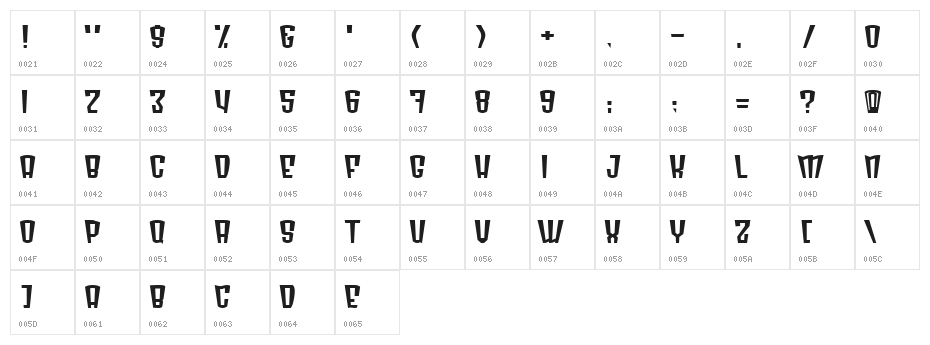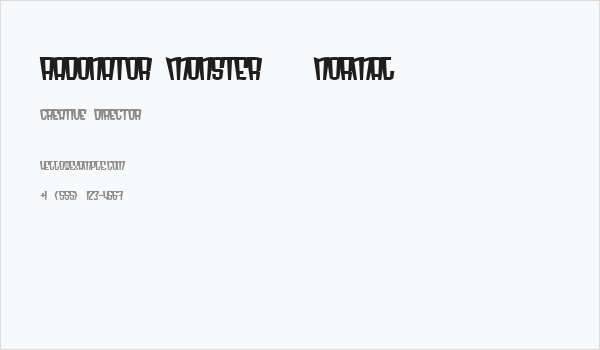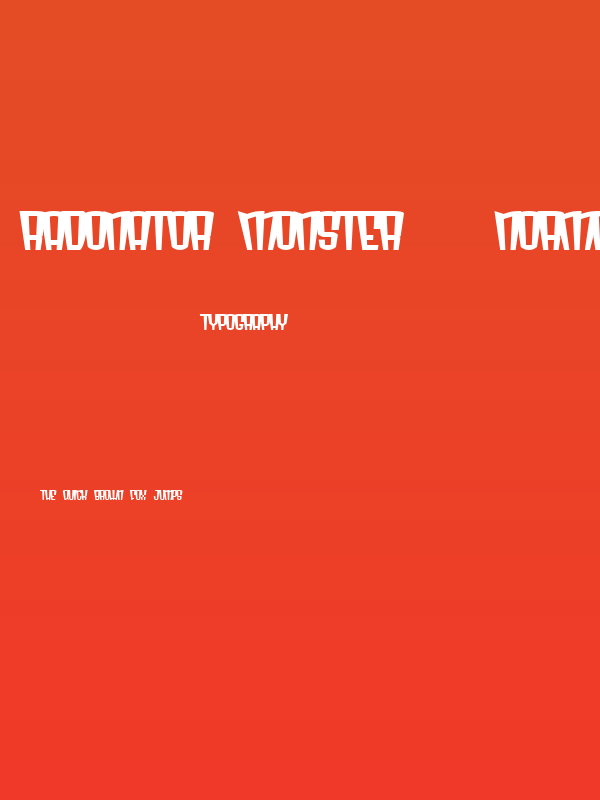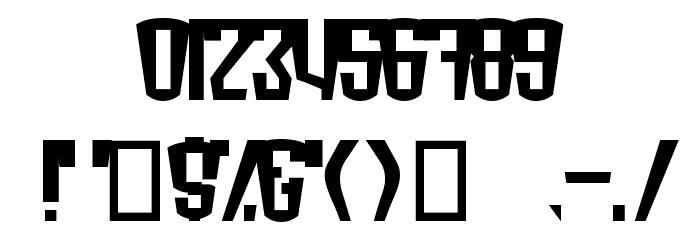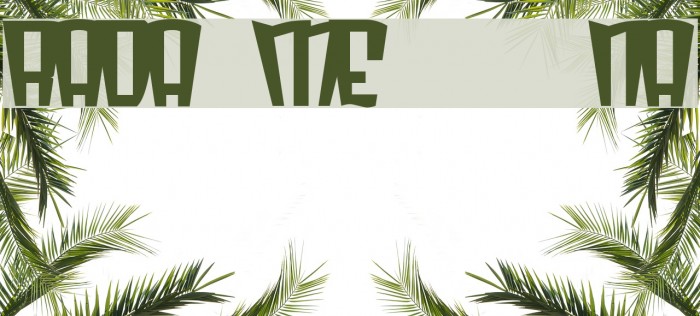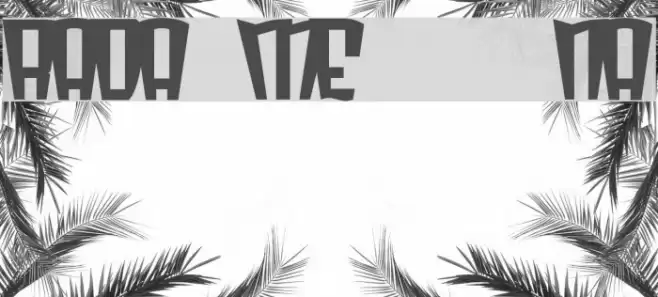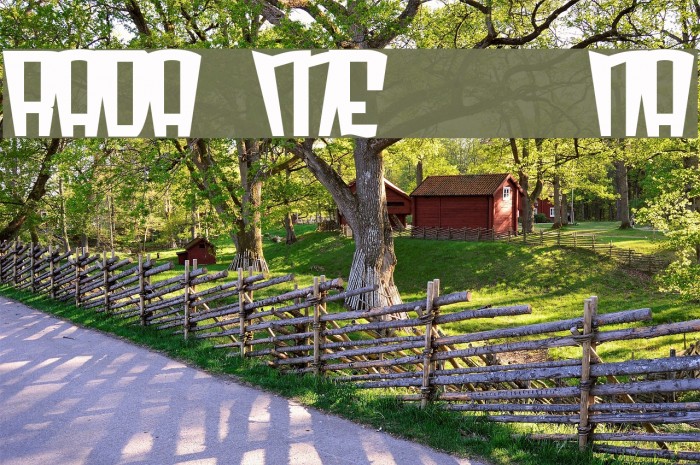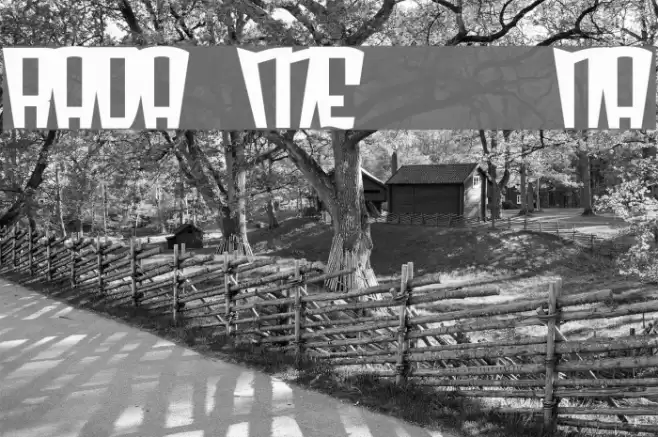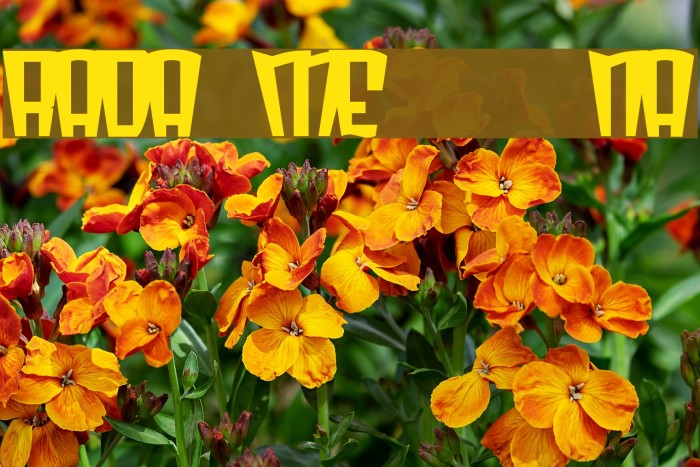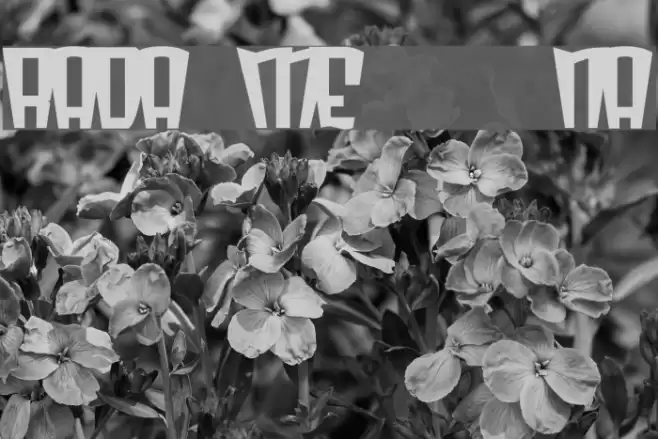
Radonator Monster Normal Font
| おすすめプロジェクト | Ideal for posters, video game titles, Halloween-themed designs, and any project needing a dramatic impact. |